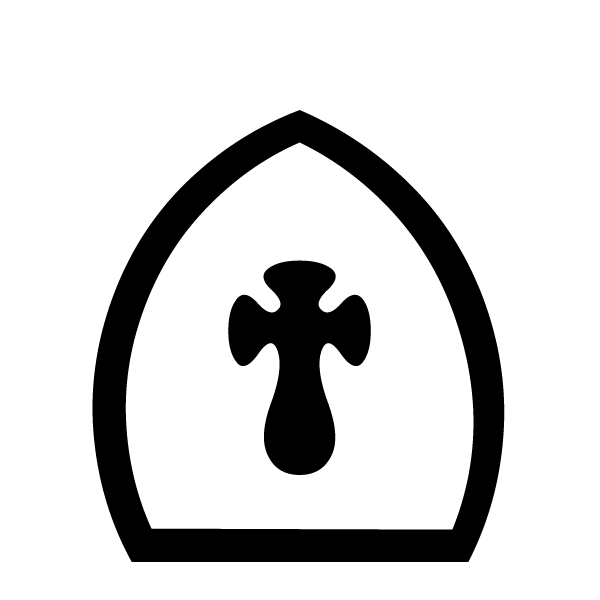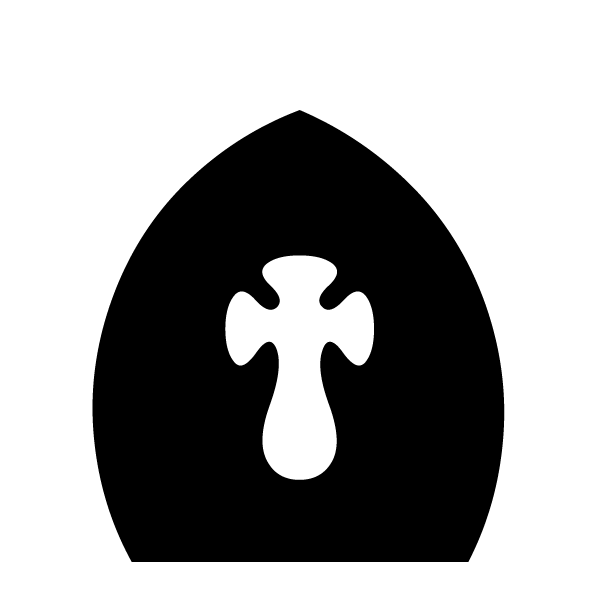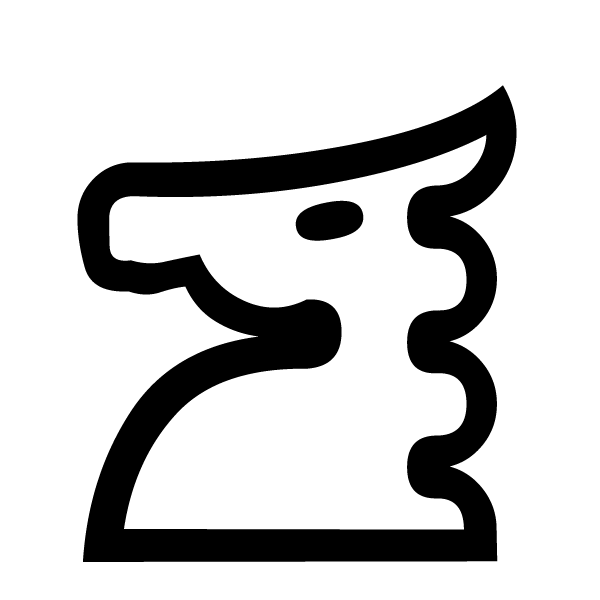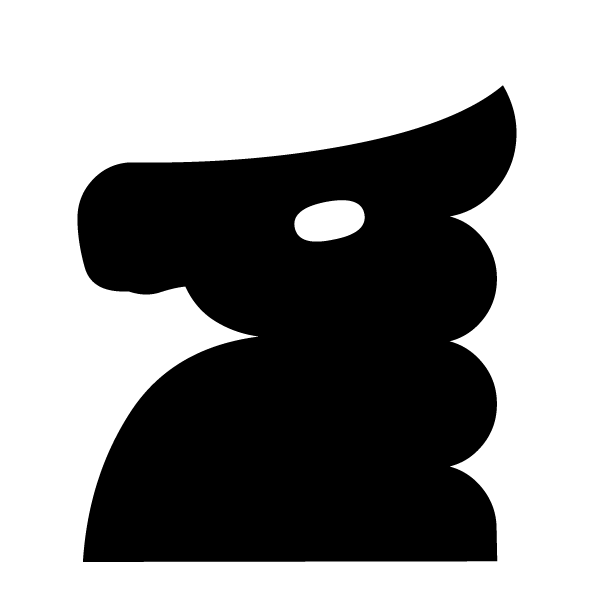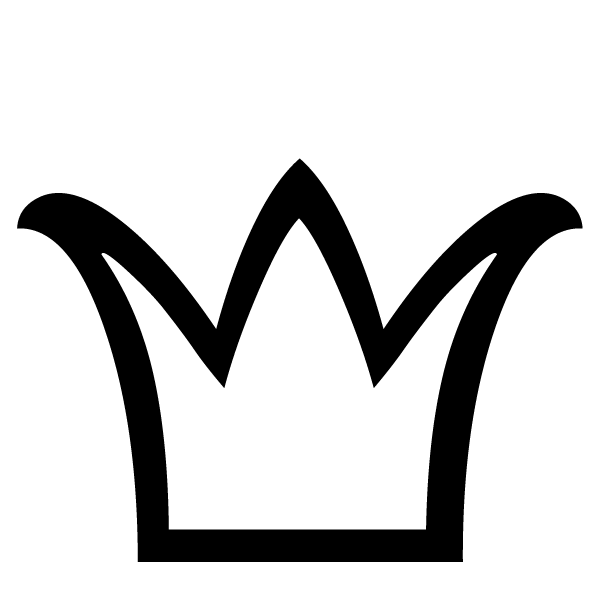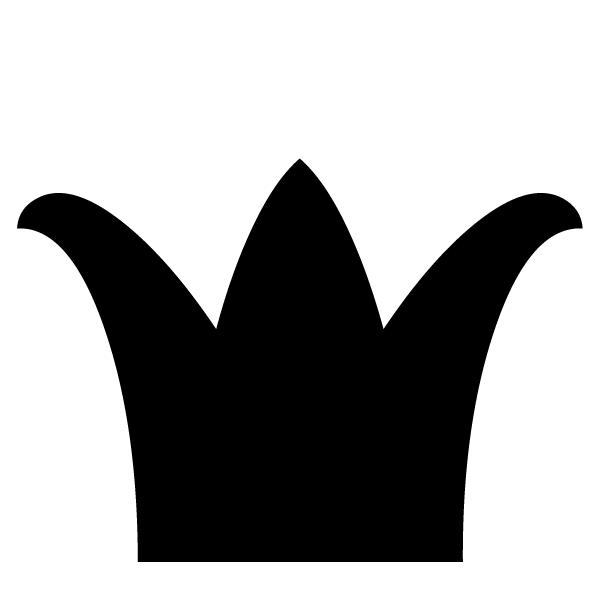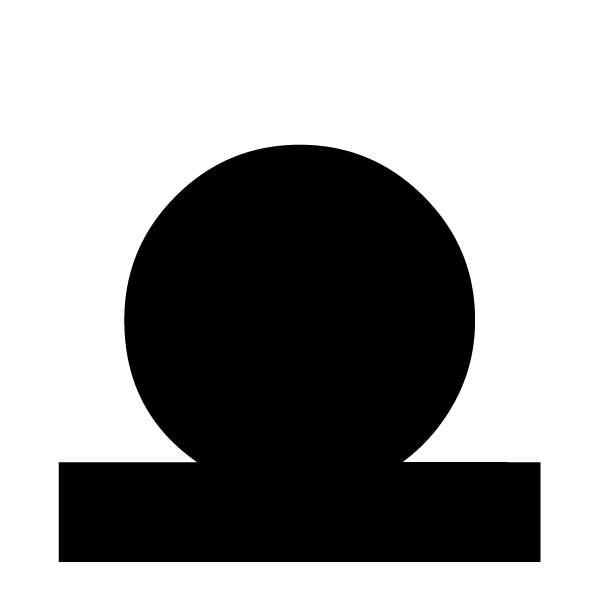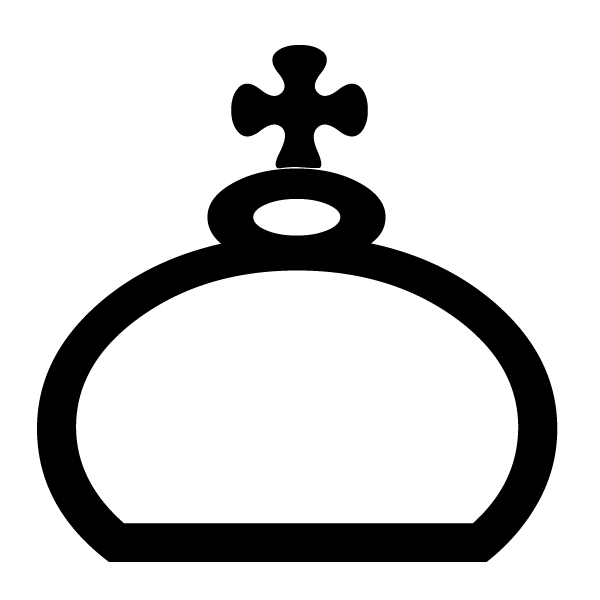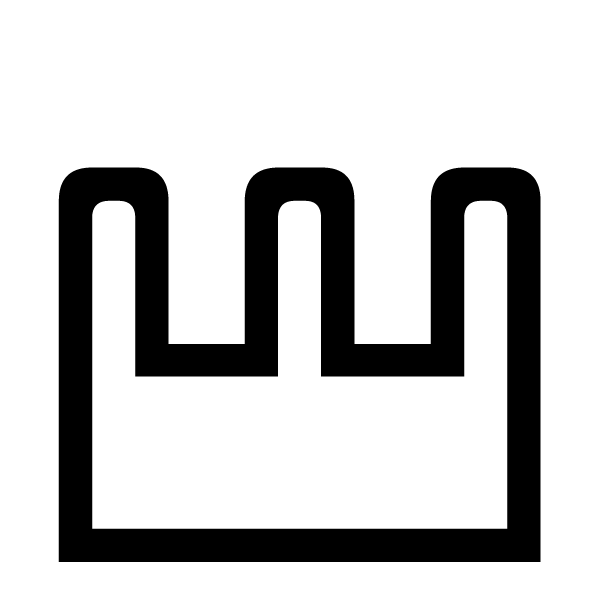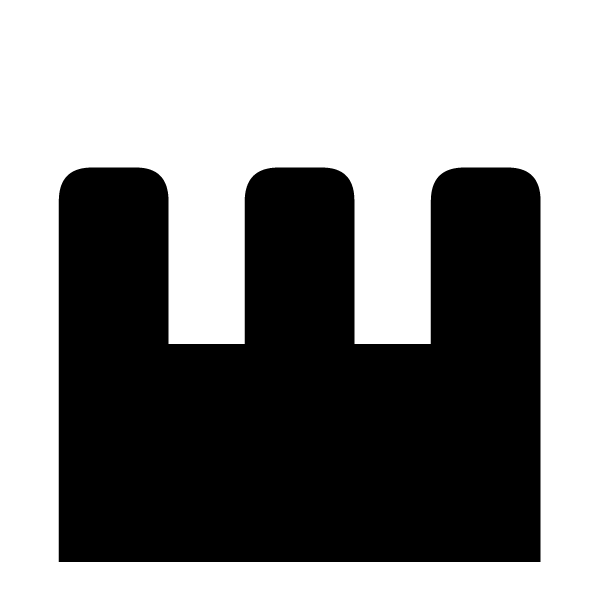
La Fuente Chess Mark se destaca por sus formas simples y esenciales que representan las piezas de ajedrez. Su diseño redundante permite una visualización clara y elegante, ideal para proyectos gráficos y temáticos de ajedrez. Esta fuente es freeware y ha sido creada por Armando Hernandez Marroquin.
Juego de Ajedrez con la Fuente Mark: